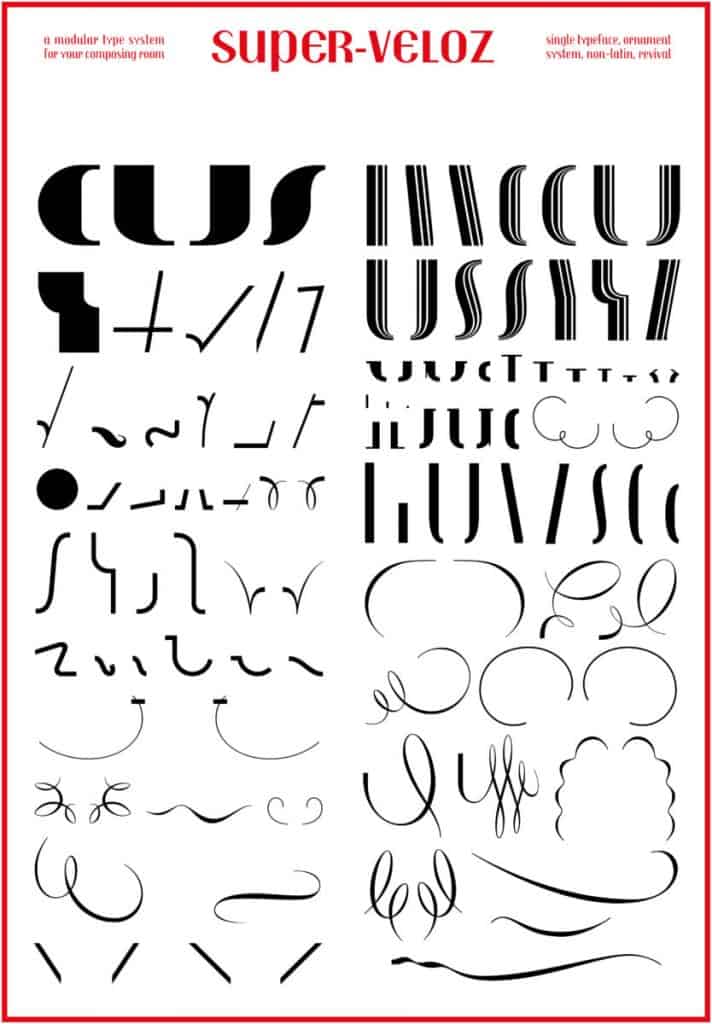
Hoy cedemos la palabra a José Luis Meliá Roger y José Luis Martín Montesinos, del Senado del Museo de la Imprenta, que comparten con nosotros la historia de la colección de tipos combinables Super-Veloz, creada por el gran tipógrafo Joan Trochut y que permite no solo crear textos, sino también ilustraciones.
Super-Veloz, vía Typerepublic.
Super-Veloz: una tipografía nacida para triunfar
Producido en 1942 por la Fundición Tipográfica Iranzo (Barcelona), el sistema modular Super-Veloz de Joan Trochut era una colección de tipos combinables diseñados «para satisfacer las necesidades de la tipografía publicitaria y decorativa», tal como se describe en el catálogo de presentación.
Un sistema que nace con la vocación de mejorar el aspecto gráfico de los pequeños impresos comerciales, tarjetas, anuncios, etiquetas o papelería comercial; reduciendo los costes de producción.
Consciente de la necesidad de obtener originalidad a bajo coste en la producción de los pequeños impresos y, probablemente, teniendo en mente aquellos tipos geométricos que todavía se utilizaban en los talleres de la época, Joan Trochut trabajó en la idea de crear un sistema tipográfico que pudiera ser utilizado no tanto para la composición de textos como para la construcción de tipos de letra –alfabetos– y que, a su vez, las mismas formas tipográficas sirvieran como recurso para ilustrar.
Super-Veloz, vía alextrochut.com
Joan Trochut describe su sistema tipográfico como un «tipo rigurosamente integral». Parte del concepto del módulo que dio origen a la tipografía y construye un sistema de elementos combinables.
Con el Super-Veloz la pieza de plomo no hace referencia a un carácter sino a parte de él. Distintos caracteres y alfabetos pueden construirse con la combinación de las distintas piezas del Super-Veloz: rasgos o elementos secundarios que se añaden a los troncos o elementos principales, dando como resultado una infinidad de posibilidades formales.
Super-Veloz, vía alextrochut.com.
La versatilidad de este sistema permitió a impresores desarrollar alfabetos, diseñar logotipos y marcas comerciales; sin las limitaciones propias de los tipos de plomo.
En el año 2004, Andreu Balius y Alex Trochut, nieto del que fuera el creador de este sistema modular, realizaron para Typerepublic una versión digital del tipo Super-Veloz, interpretando con máxima fidelidad los originales de Joan Trochut.
Super-Veloz, vía alextrochut.com.